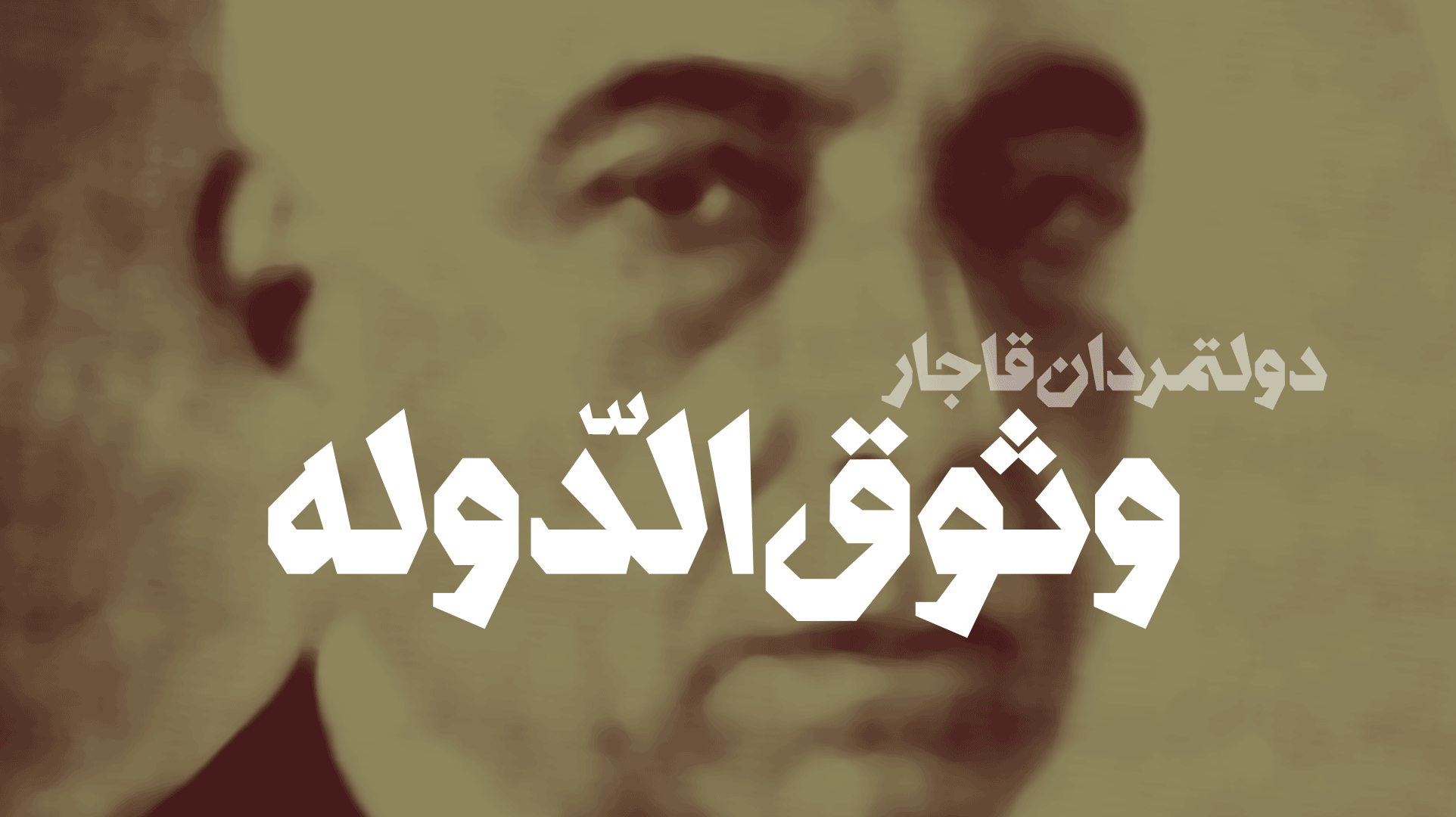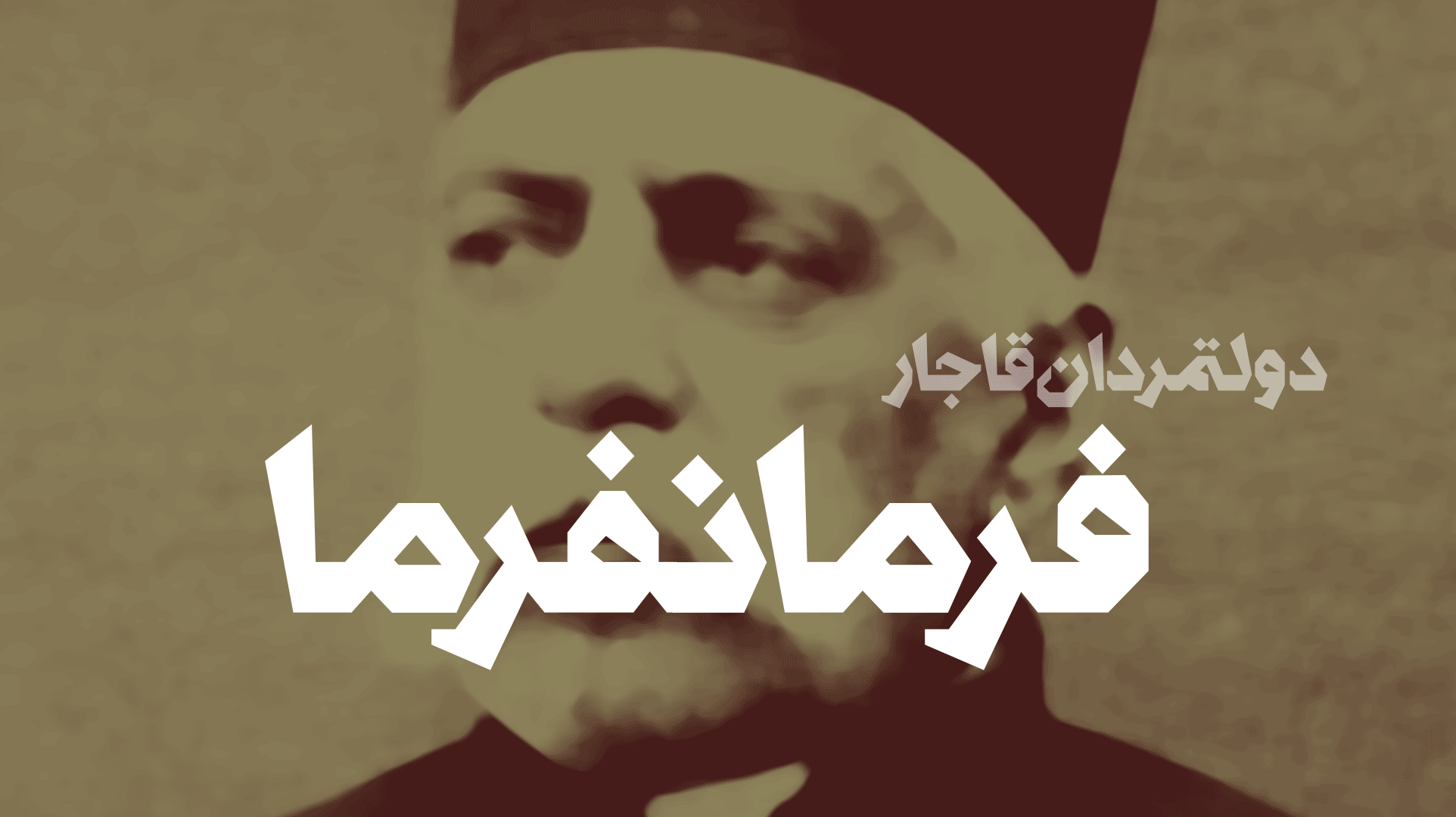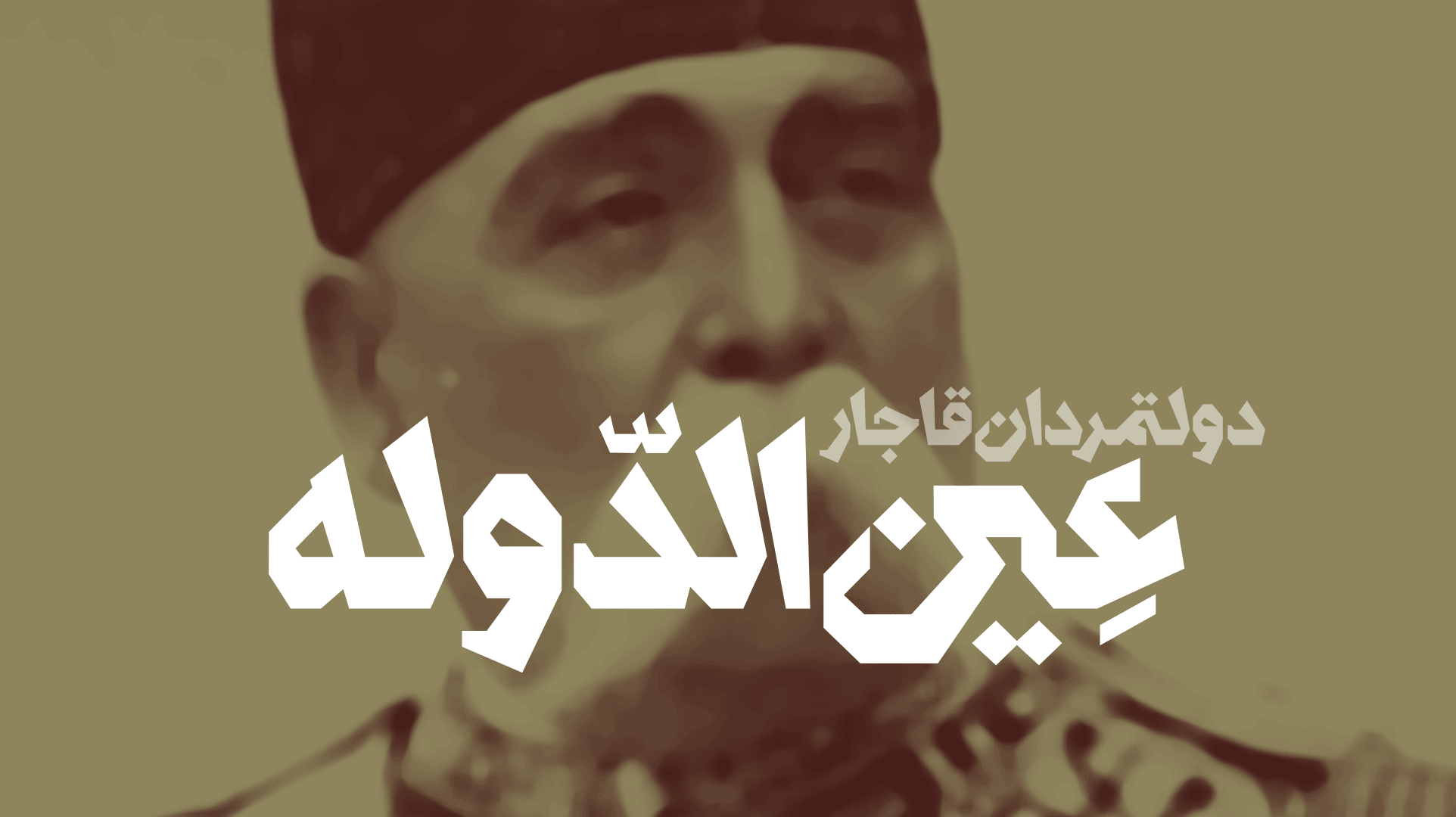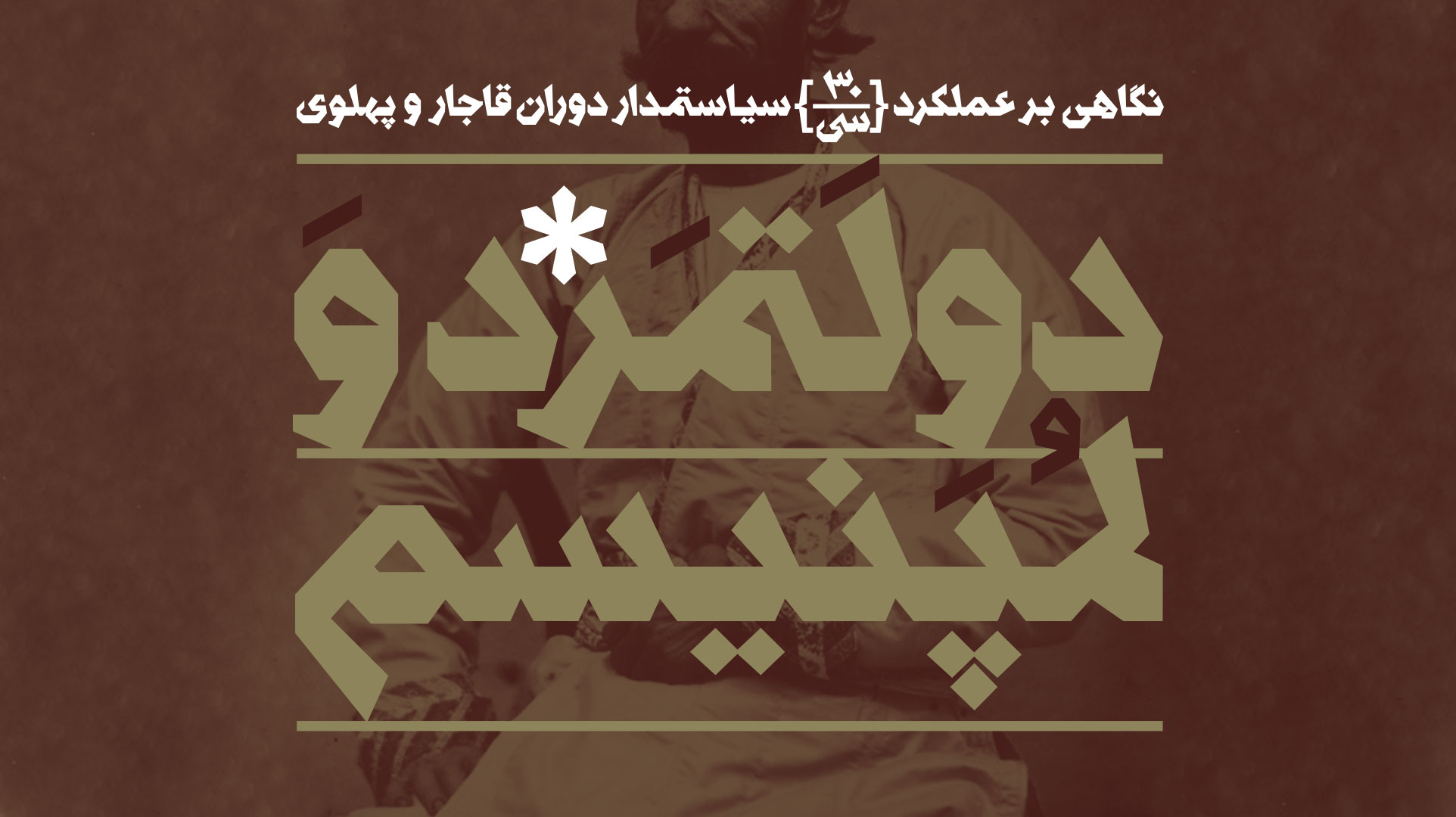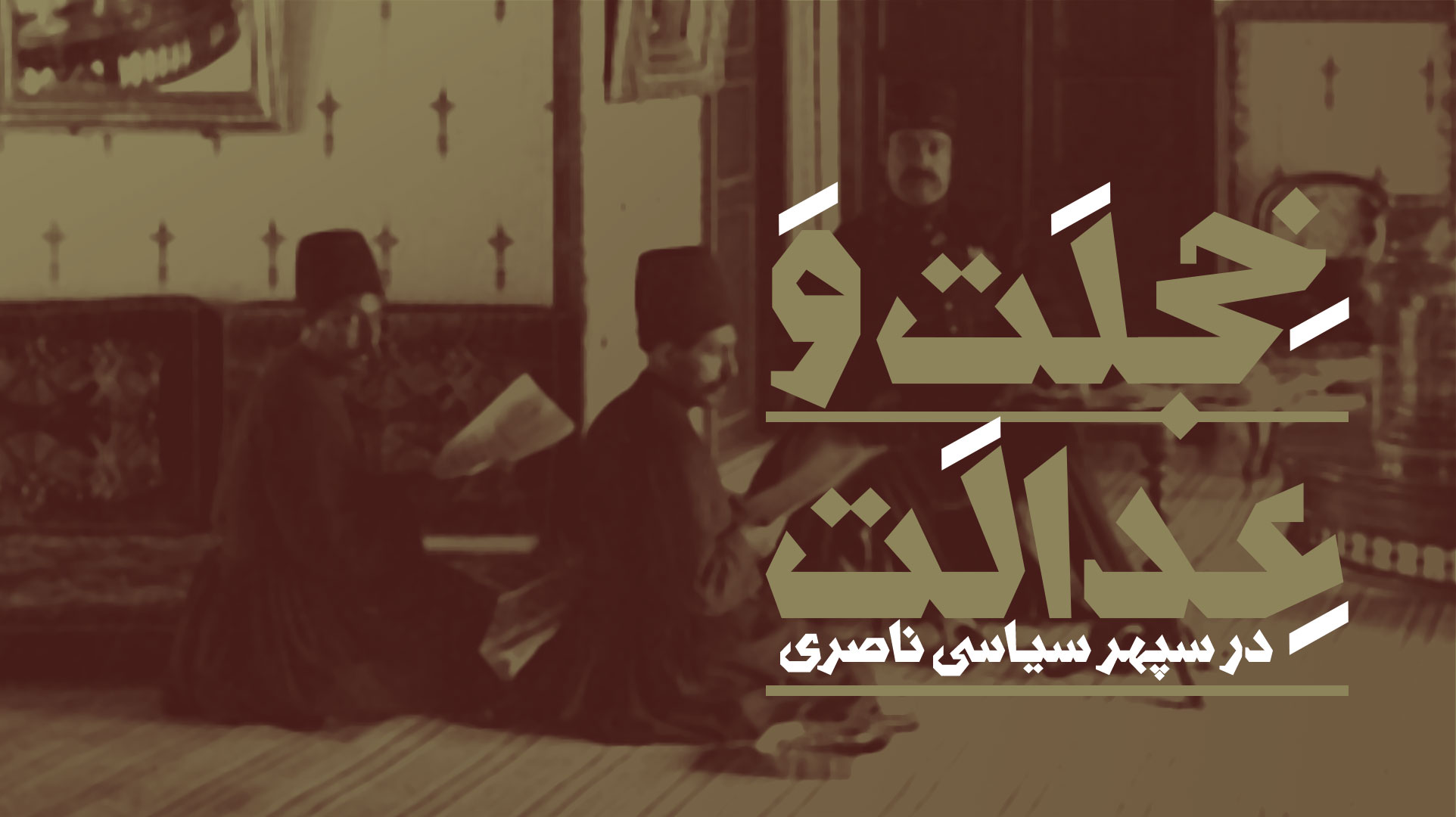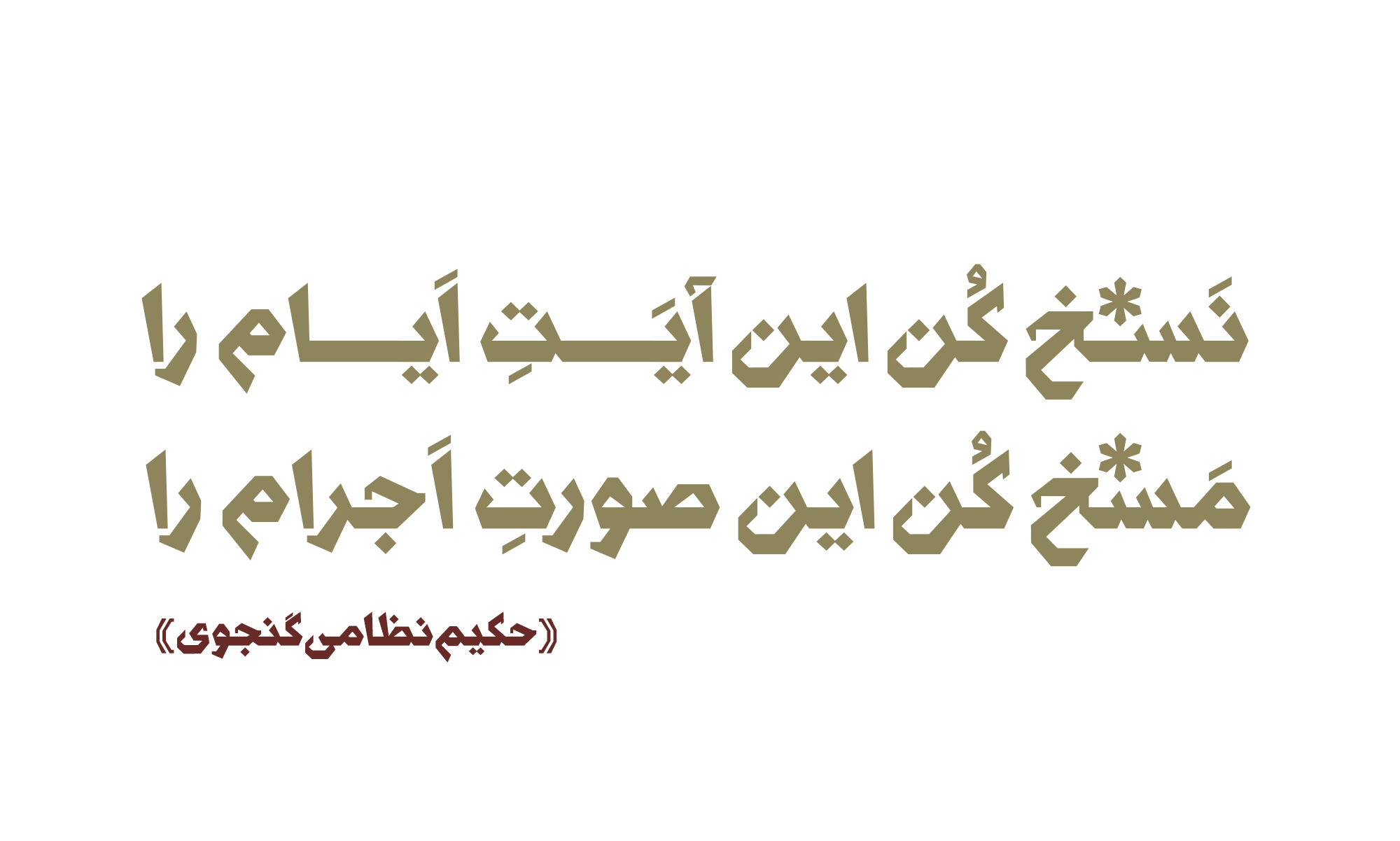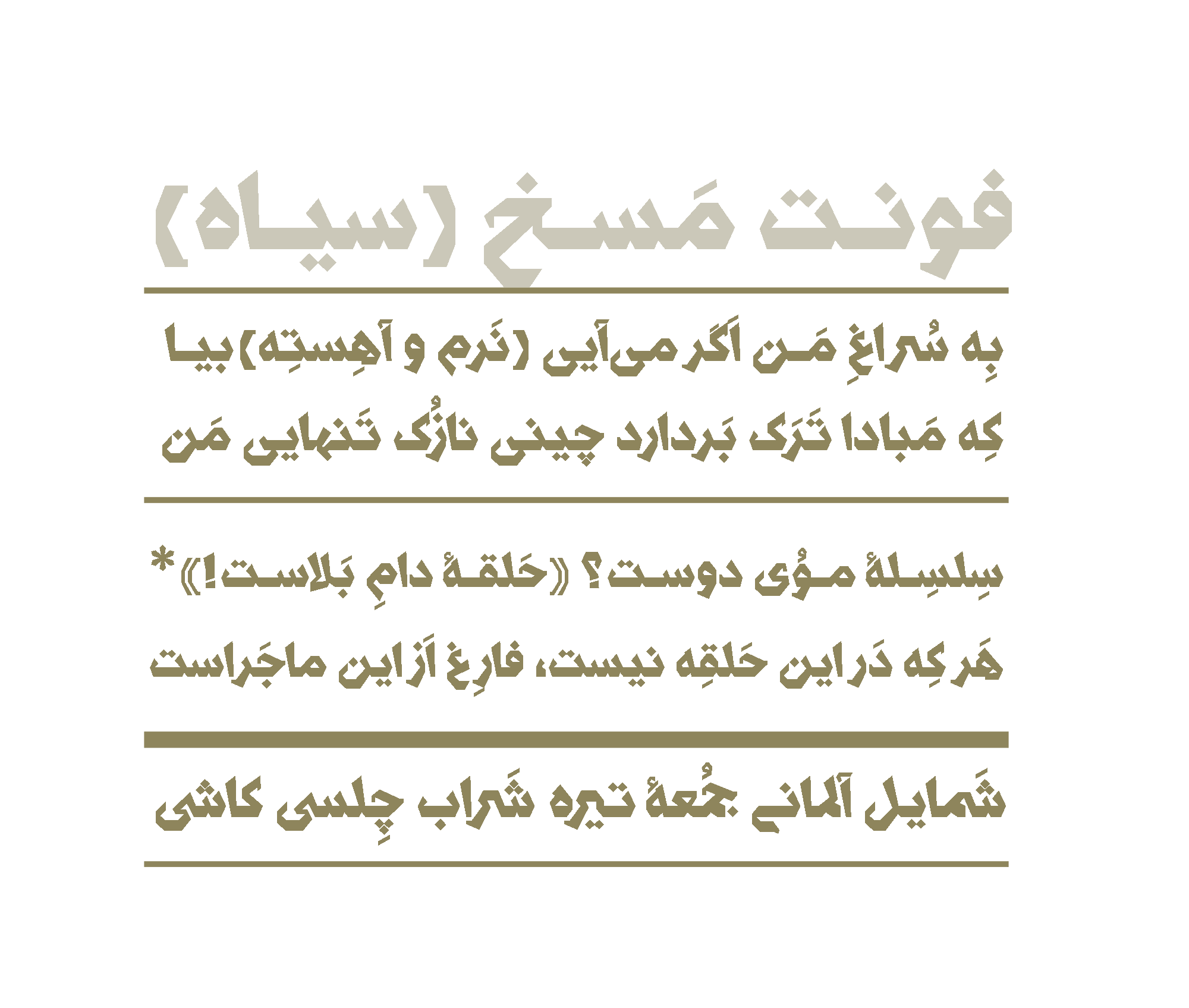
کاستهشدن کشیدگیهای عمودی حروف (نزدیکشدن دو محور Ascent و Descent به خط کرسی)، درشتترشدن بخش نشسته بر خطِ کرسیِ حروف، ضخامتیافتن تیغههای انتهایی حروف، به کارگیری زوائد تزئینی محدود و کنترلشده (مثلا در حروف ر، و، د) و نیز استفاده از قواعد مشترک در زوایا، ضخامت و چرخش حروف (مثلا شباهت قوسهای مثبت و منفی حروف به یکدیگر، شباهت دندانهها، چشمیها و… تا حدی که این مشابهتها باعث نازیبایی حروف در ترکیبات نگردد) از دیگر ویژگیهای شکل فونت مسخ است. ویژگیهایی که باعث ایجاد توازن و تیرگی یکدست در عبارتنویسیها میشود.